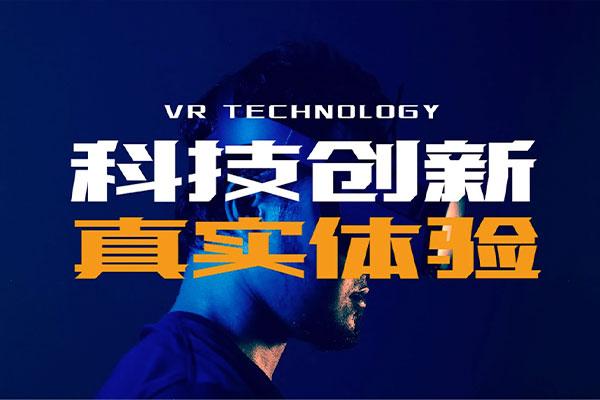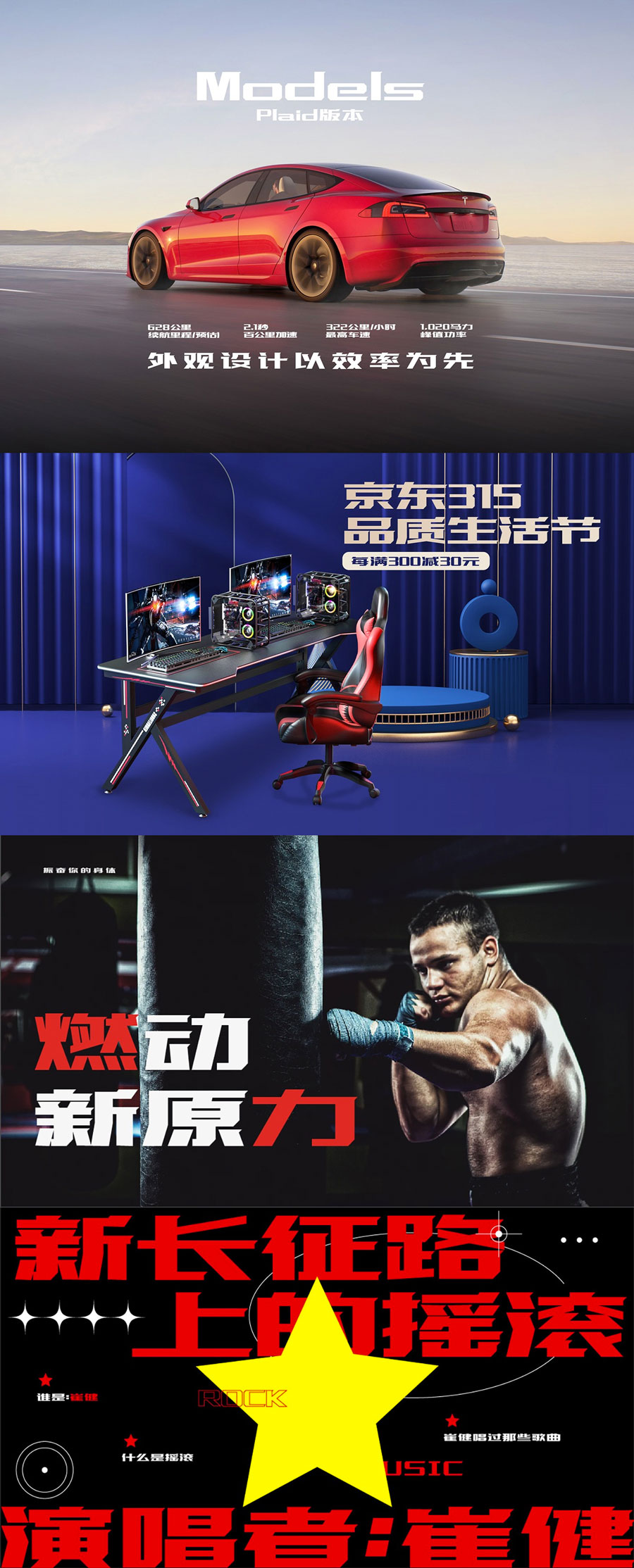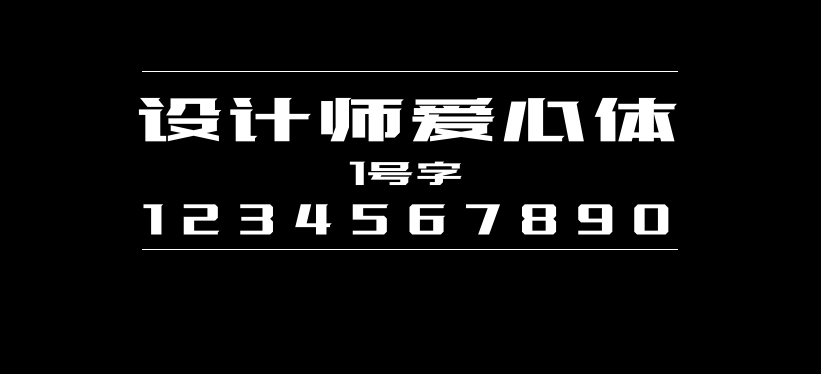
设计师爱心体1号字
设计师爱心体1号字是为了能够更好地服务困境儿童,让他们的未来有更多的可能性,弥补他们学习生活中艺术教育的缺失,字体设计师刘兵克与历下区未成年人救助保护中心合作,为历下区困境儿童设立设计师公益基金,于2021年6月发布。
设计师爱心体,源自“困境儿童”公益活动。由设计师刘兵克发起这个项目,并设计最初的字形规范及基本部首,最终,一套好用且免费的中文字体“设计师爱心体1号字”诞生,并在2021年6月发布。
在未来的日子里,刘兵克将会带领他的团队持续开发多套字库作品,设计师爱心体1号字只是开始,未来会出现设计师爱心体2号字、3号字、4号字、5号字……而每一套爱心字库,将会帮助和捐助予不同的受助对象。
“设计师爱心字库,一方面可以让设计师有更多的字库选择,另一方面,也让大家通过对爱心字库的捐助与下载,为公益事业献上爱心,这是一件美好和温暖的事情。我非常期待1号字能够得到大家的认可,说实话,也更期待1号字能完成目标捐款金额。如果能够顺利完成,这会给我们带来更大的勇气和信心,爱心字库这份事业,我们会更有劲头的做下去!”
设计师爱心体1号字
在去年,我跟几位朋友谈起这个想法的时候,大家都表示完全可行,也全力支持我这样做。
我在济南的一位好友武林,他们公司长期为济南市历下区善治公益发展中心提供设计支持(以下简称“历下善治”),在他的介绍之下,我联系到了“历下善治”, 把公益字库的想法告诉了对方。
与期待中的一样,“历下善治”的负责人孙璐璐老师,完全认可我的想法,经过几次的面谈和交流,她们给出了很多建议,我们也共同确定了本次公益字库的捐助对象:
设计师爱心体1号字
在这里,有必要对困境儿童这个词汇进行解释:
困境儿童是指不满18周岁,因自身和家庭原因而陷入生存、发展和安全困境,需要政府和社会予以关心帮助的儿童。主要包括:
一,孤儿;
指失去父母或查找不到生父母且未被依法收养的未成年人;
二,父母监护缺失的儿童;
比如父母双方服刑在押或强制隔离戒毒(刑期、戒毒期在6个月以上,下同)的儿童;父母一方死亡或失踪,另一方服刑在押或强制戒毒的儿童;
三、父母无力履行监护职责的儿童;
比如父母双方重残、重病的儿童;父母一方重残、重病,另一方死亡、失踪、服刑在押、强制戒毒、弃养的儿童等;
四、重残、重病及流浪儿童;
比如二级以上残疾或三级四级精神、智力残疾儿童,或三级以上预防接种异常反应残疾儿童;患重大疾病的儿童;
据“历下善治”提供的数据,我所在的济南市历下区,困境儿童现状是这样的:
设计师爱心体1号字
这些儿童,在生活和学习方面,都遇到了不同程度的困难,每个孩子正处于不同的困境当中。
“历下善治”作为辖区内的公益机构,长期在为这些孩子提供帮助,她们将孩子与更多的孩子联系到一起参与服务,避免将孩子特殊化,她们重视儿童的全面发展,尤其是文化课学习和艺术课程方面的辅导,希望每一个孩子都不掉队:
设计师爱心体1号字
而我们这次发布的公益字体,目的也很明确:
通过设计师群体的爱心捐助,弥补困境儿童在学习生活中艺术教育的缺失,让他们感受到艺术的美好与快乐,让他们感受到社会的温暖,给他们更多的信心和和勇气。
爱心捐助款项,会用于困境儿童的艺术课程包(艺术课程+学习用具),提高他们的艺术素养,提升他们的表达能力和交往能力。
设计师爱心体1号字